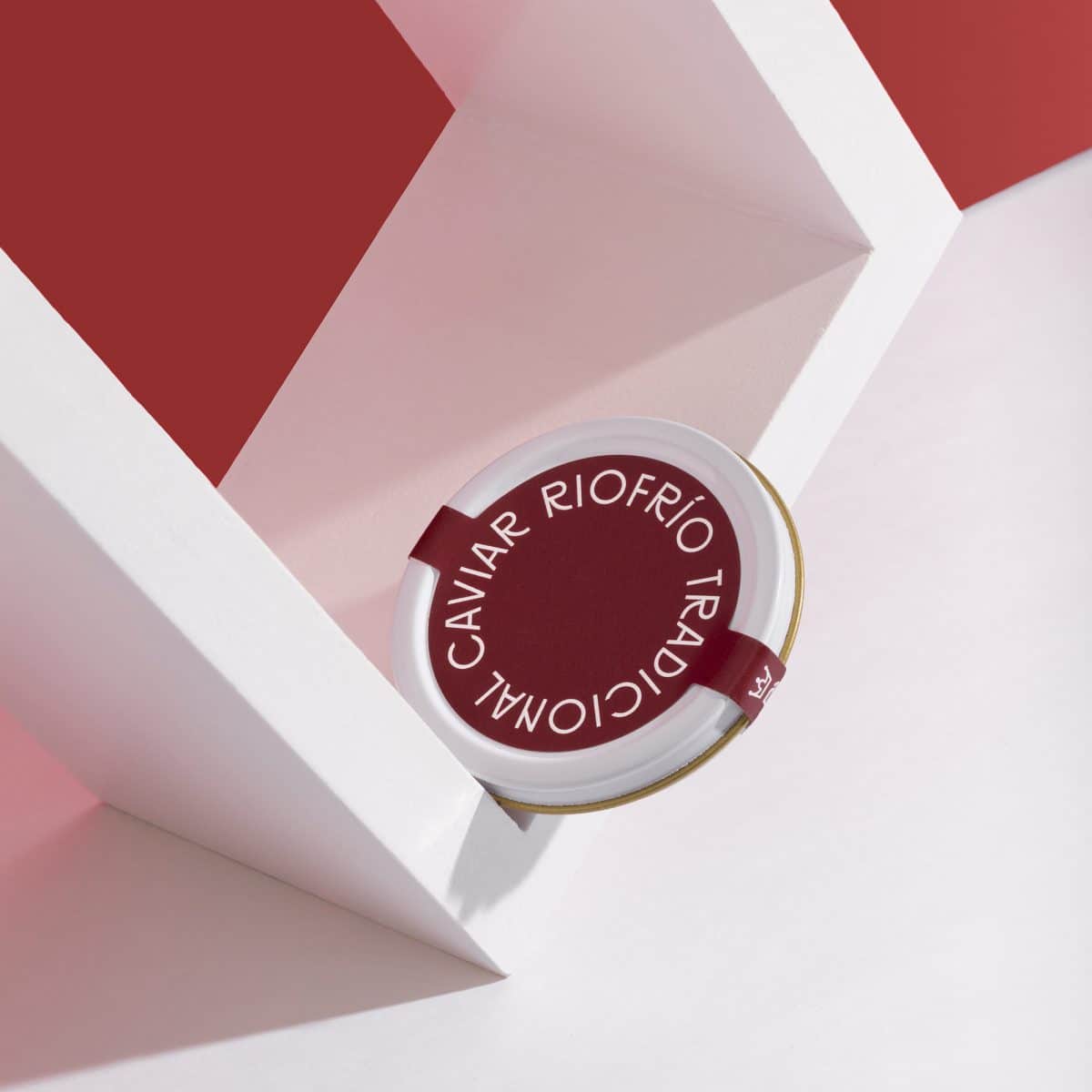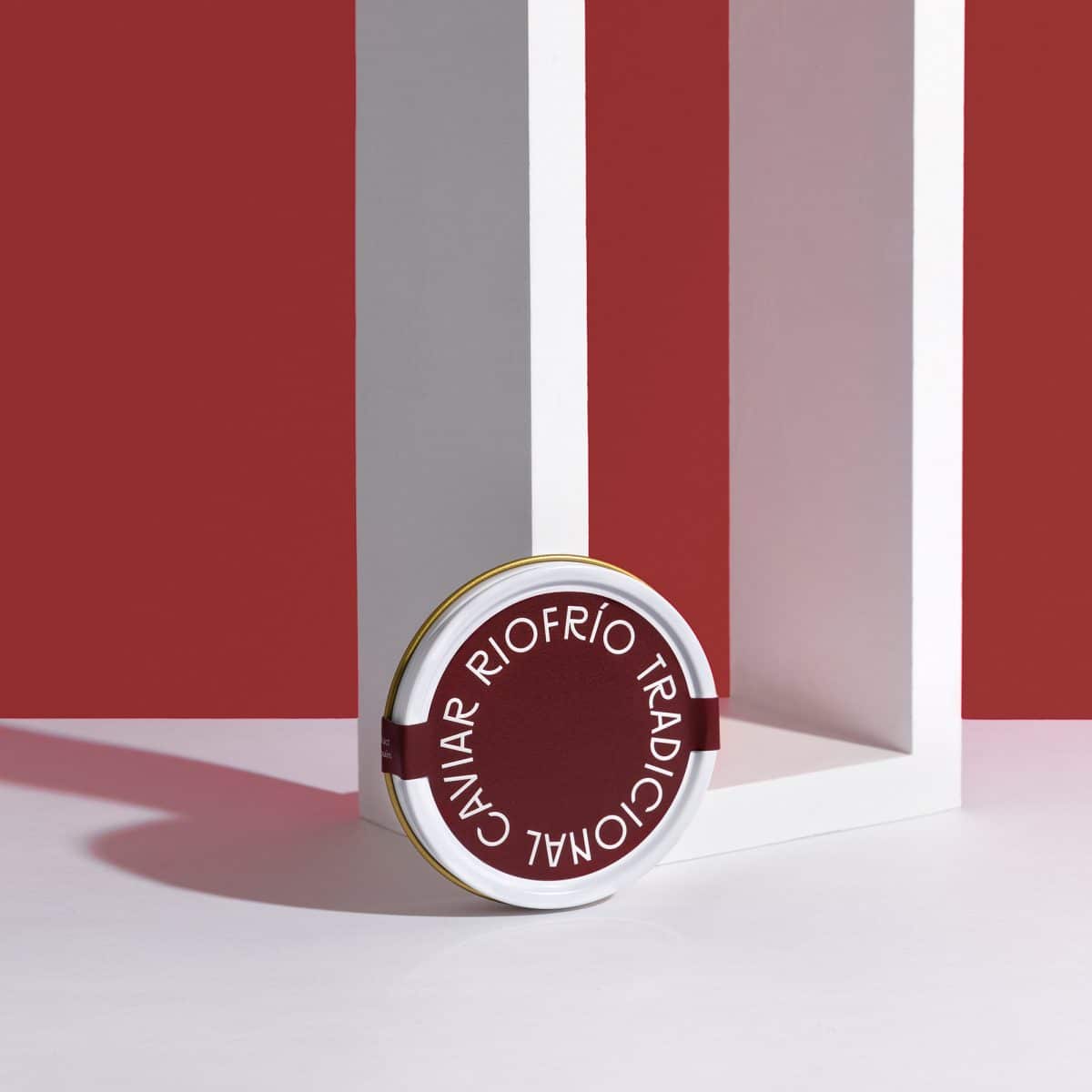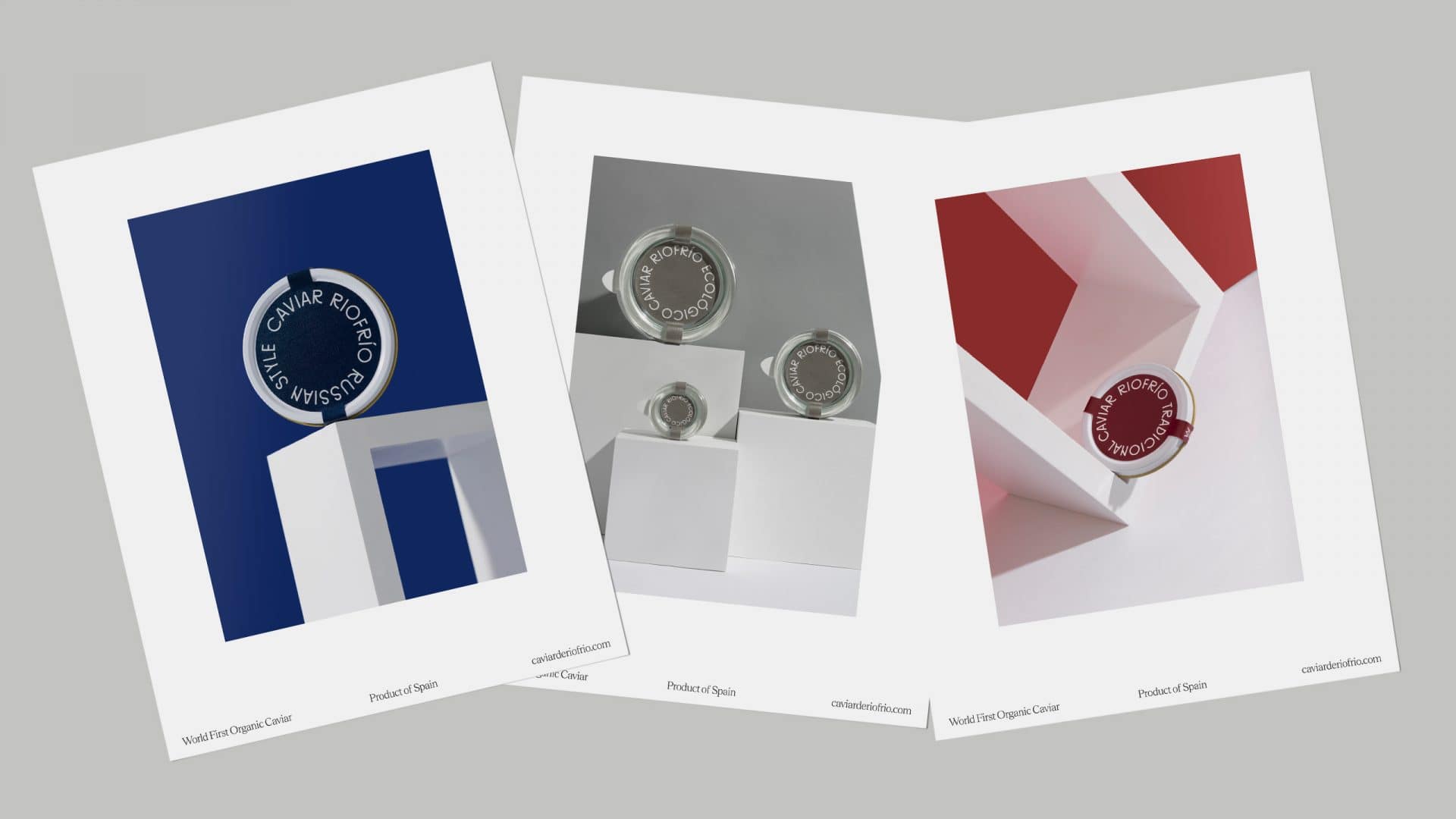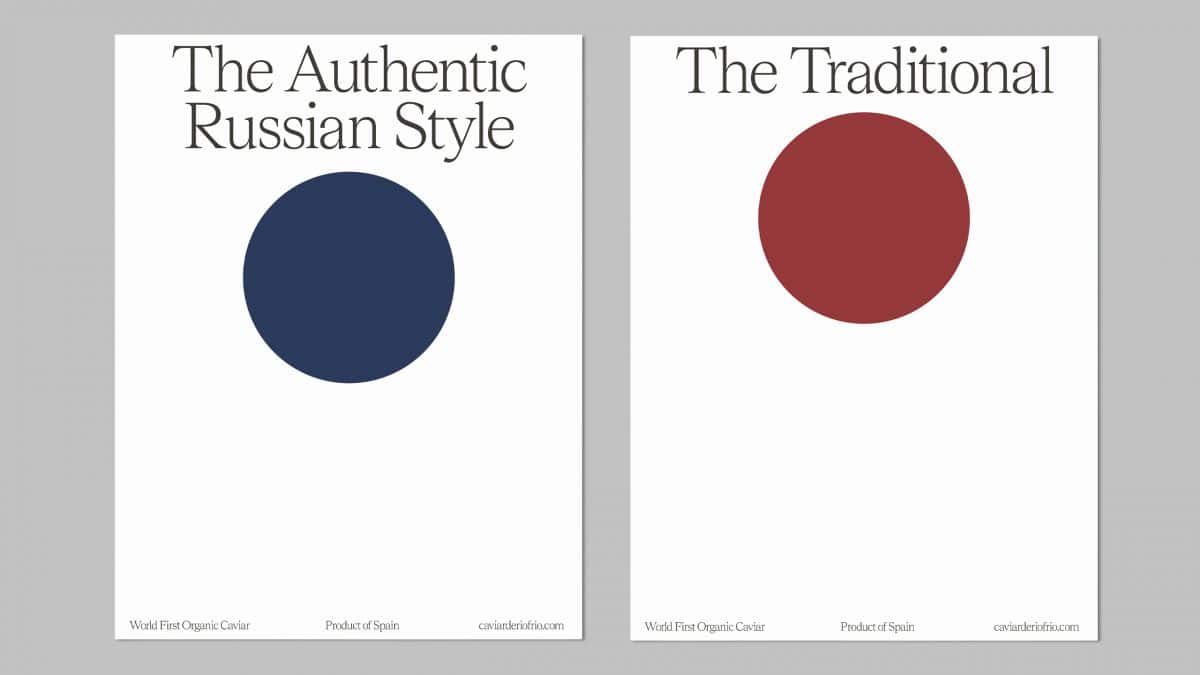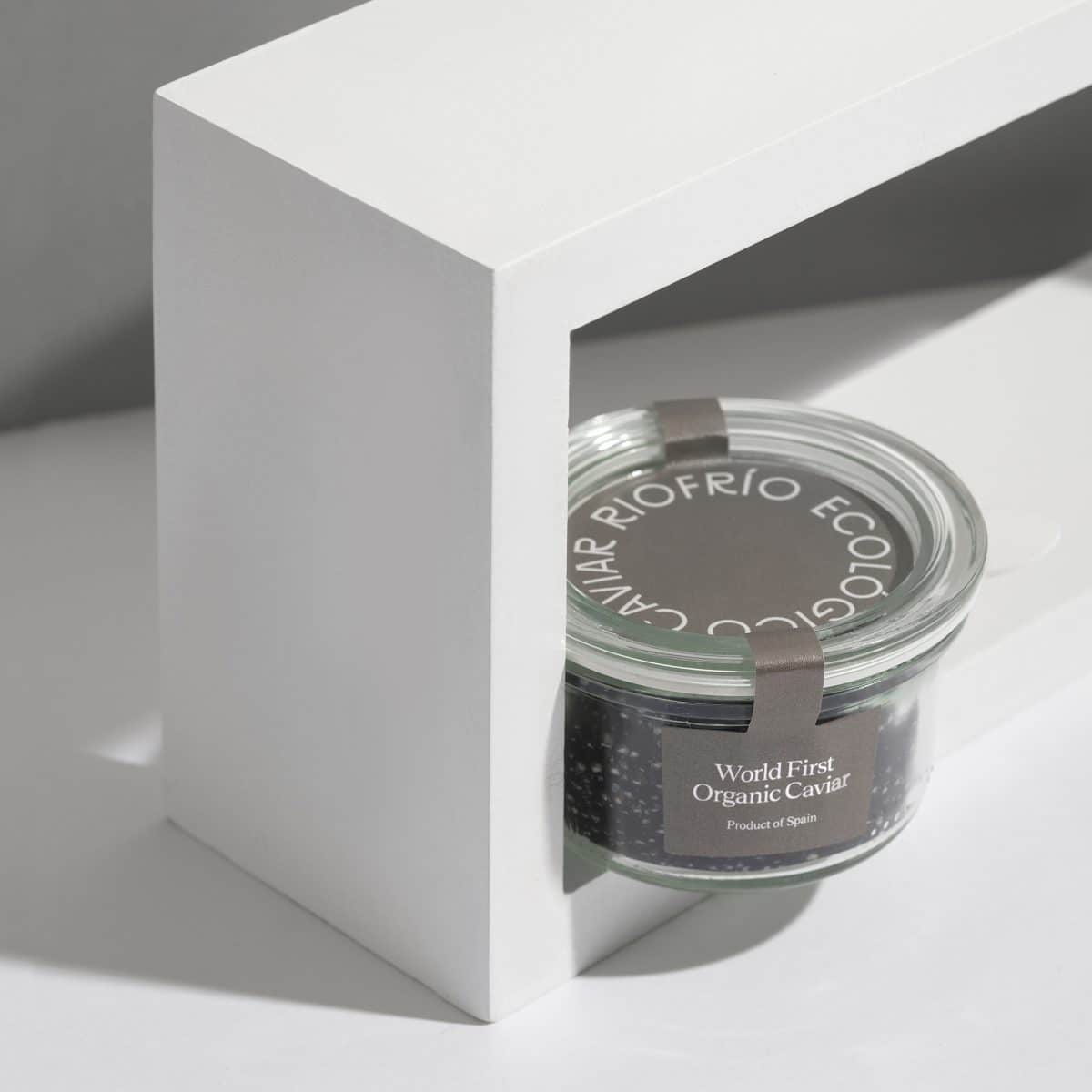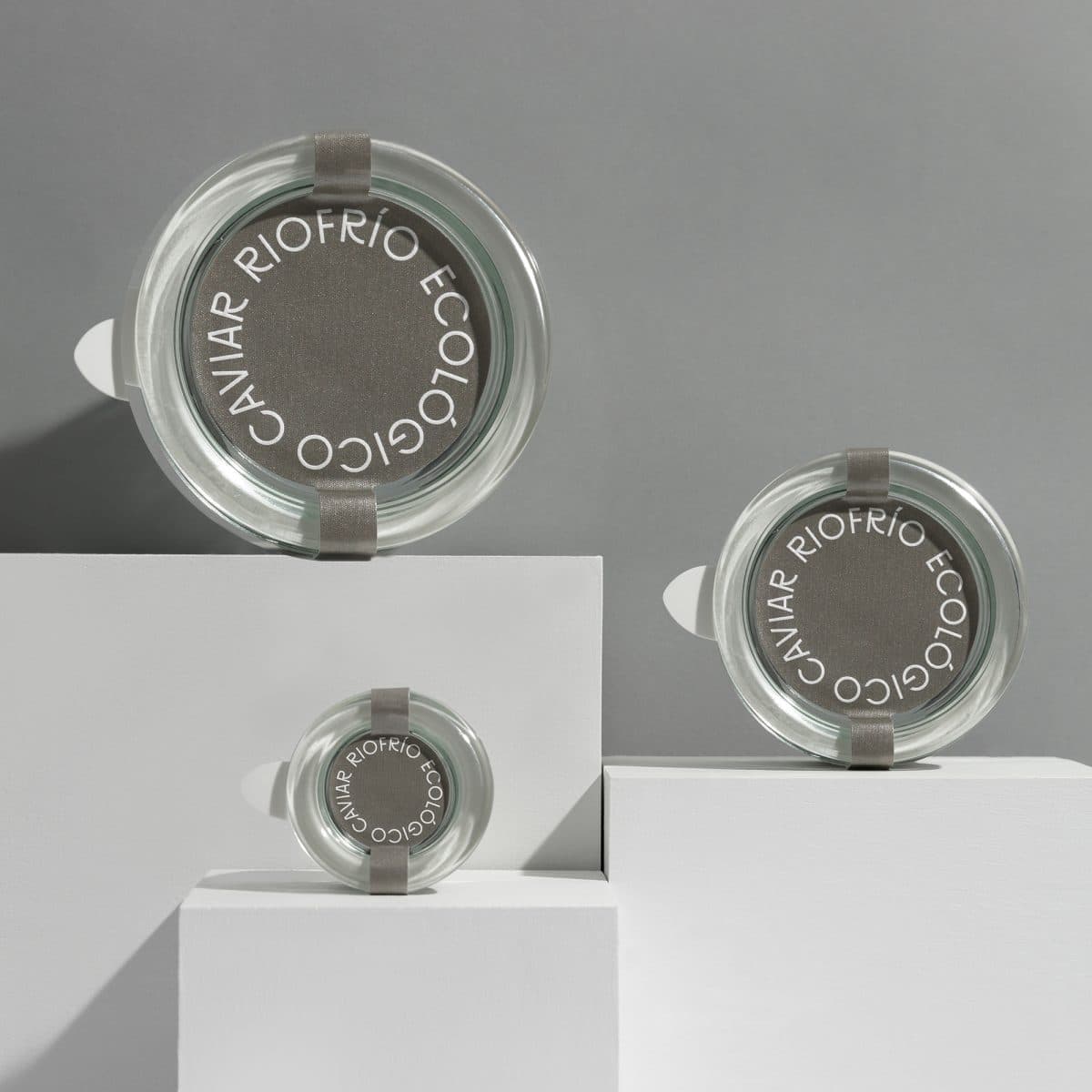
O estúdio de design granadino Buenaventura mergulhou nos estimulantes anos 20 do século passado para encontrar a inspiração de que necessitava para o rebranding e a revisão integral da imagem da marca Caviar de Riofrío.
Fundada em 1963, a Caviar de Riofrío, referência mundial no setor do luxo e da alta cozinha, é um dos principais aquicultores de esturjão da Europa, e o primeiro com certificação ecológica para caviar. Após uma longo percurso, necessitava de um rebranding integral que se traduzisse numa nova identidade visual e num novo design de embalagem e de suporte editorial.
Para o seu rebranding, os granadinos deixaram-se influenciar pelos ensinamentos da escola Bauhaus: em 1923, um dos seus grandes mestres, László Moholy-Nagy (1895-1946), escreveu um pequeno ensaio em que aprofundava o tema do papel da tipografia e no qual afirmava que esta “deve ser a comunicação na sua forma mais intensa”.
O ensaio contou-lhes o segredo que procuravam para dar forma ao seu projeto. A partir dessa ideia, o estúdio Buenaventura criou um sistema visual tipográfico baseado no movimento dos esturjões que finaliza adotando a forma circular, ícone do universo do caviar.
O sistema funciona integrando cada uma das suas receitas na própria marca, colocando o ênfase na clareza absoluta. Também a codificação cromática desempenha um papel fundamental em todo o conjunto visual.
Para o design de embalagem, o estúdio Buenaventura escolheu o papel Constellation Jade Raster, fabricado com celulose pura ECF® e caracterizado por um acabamento perolado numa das faces, permitindo que o efeito final de todo o conjunto seja altamente inspirador. Para o elemento de suporte visual o estúdio escolheu Oikos e Constellation Jade.